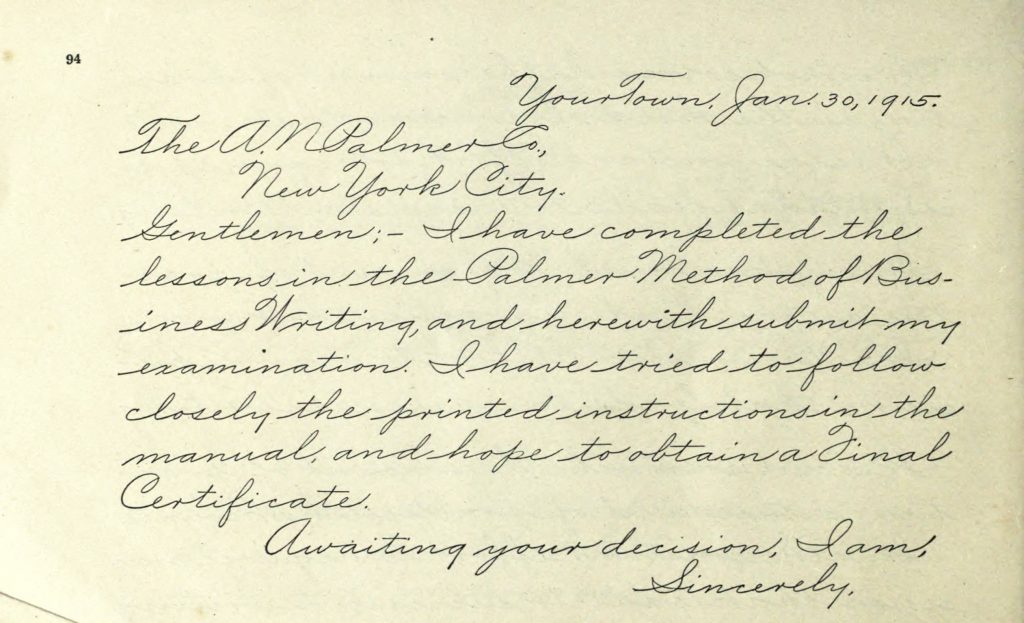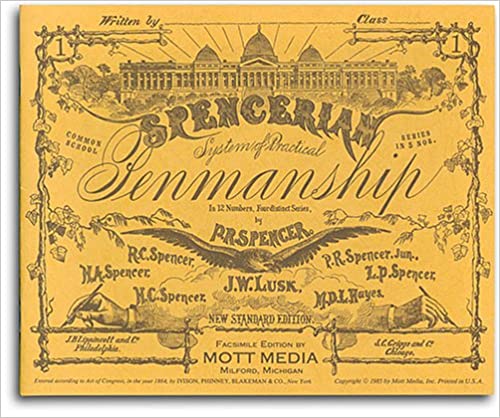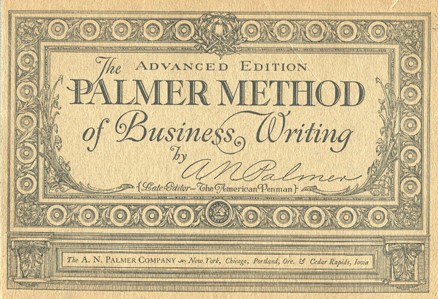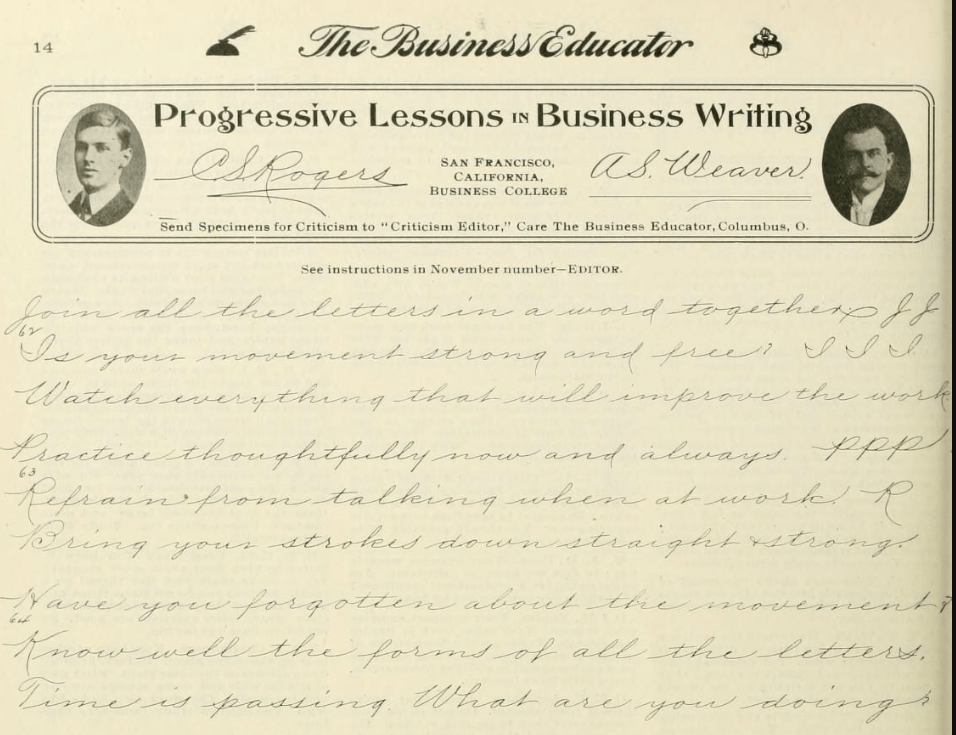
Il y a quelques mois, je vous parlais de mon apprentissage de la Spencerian et de l’écriture cursive américaine. Je vous avais promis un article dédié à cette écriture, le voici enfin ! Préparez-vous à plonger dans l’histoire, au cœur de la révolution industrielle et du développement des affaires !
La Spencerian, une écriture dans son temps
Au cœur de la révolution industrielle
Au début du XIXème siècle, l’écriture enseignée aux Etats-Unis et en Europe était principalement issue de l’Anglaise (ou Copperplate). Avec l’essor de l’industrie et du commerce, les besoins d’écriture pour les affaires se développèrent. Dans les banques, les sociétés de courtage, les assurances, les postes et les industries, la rédaction des contrats, des lettres et la tenue des registres employèrent de nombreuses personnes dont le métier était…d’écrire.
L’essor des plumes métalliques
Concomitamment, dans les années 1830, le procédé de fabrication industriel des plumes métalliques fut au point. Développé par les anglais Gillott et Perry, il offrit une plus grande diffusion des outils d’écriture pour les services administratifs et les écoles, en même temps que de meilleures facilités d’écriture qu’avec la plume d’oie qu’il fallait retailler sans cesse et qui était très fragile.
La naissance de la Spencerian
L’enseignement de l’écriture manuscrite se développa massivement, dans le sillage de la démocratisation de l’enseignement. Savoir écrire devenait un prérequis pour nombre d’emplois administratifs de la société industrielle ainsi qu’un outil d’émancipation sociale.
Vers 1840, Platt Rogers Spencer, un enseignant américain, se consacra à l’étude et la mise au point d’une écriture cursive fonctionnelle qui répondrait mieux aux besoins de l’époque : il simplifia considérablement l’anglaise en s’affranchissant notamment des pleins et déliés, des boucles complexes et des majuscules ornementées. Le système d’écriture qu’il proposa alors privilégiait à la fois la lisibilité, une plus grande rapidité d’exécution, sans sacrifier la beauté calligraphique. Sa méthode devint la norme, et la Spencerian fut enseignée à travers tous les Etats-Unis.
L’héritage de Roger Platt Spencer
Spencer mourut en 1864, mais de nombreux maîtres calligraphes perpétuèrent l’enseignement de sa méthode. Deux des principaux modèles pédagogiques qui ont marqué l’histoire du Spencerian sont les suivants :
La méthode Palmer : business first !
Vers 1890, Austin Norman Palmer édita une méthode d’écriture qui simplifiait encore la Spencerian, avec une méthodologie d’apprentissage privilégiant la posture et le mouvement du bras entier plutôt que le mouvement des doigts et du poignet pour accompagner l’écriture.
La Méthode Palmer fut rapidement reconnue et adoptée, pour sa simplicité et sa rapidité. Elle permettait (presque !) à l’écrivain de rivaliser avec la machine à écrire, mais surtout de pouvoir écrire pendant longtemps sans éprouver de fatigue ou de crispation musculaire. De quoi satisfaire le besoin de productivité des bureaux administratifs et commerciaux : business first !
En 1912, sa méthode fut vendue à plus d’un million d’exemplaires et devint la nouvelle norme d’enseignement de l’écriture aux Etats-Unis jusque dans les années 1950.
Le modèle Zaner-Bloser
Un autre modèle pédagogique important est le Zaner-Bloser, développé par Charles Paxton Zaner et Elmer W. Bloser. Bien que le Zaner-Bloser ne soit pas strictement basé sur le Spencerian, il s’en est grandement inspiré et a incorporé certaines de ses caractéristiques dans un système d’écriture cursive largement utilisé dans les écoles américaines. Ce modèle a également contribué à populariser l’écriture cursive et a apporté des améliorations pour s’adapter aux besoins des élèves.
Caractéristiques de l’écriture Spencerian
Le Spencerian se caractérise par des traits élégants, des courbes douces et un aspect fluide qui donne à l’écriture une touche artistique. Voici quelques-unes des principales caractéristiques de cette écriture :
Formes courbes et gracieuses
Les lettres de la Spencerian sont principalement formées de courbes gracieuses, ce qui donne à l’ensemble de l’écriture un aspect harmonieux et élégant. Les lignes fines et les boucles délicates lui confèrent une beauté artistique qui la distingue des styles d’écriture plus rigides.
Connexions fluides
Un aspect essentiel du Spencerian est la liaison fluide entre les lettres. L’écriture est conçue pour être réalisée d’un seul trait, sans lever le stylo, créant ainsi une continuité esthétique entre les caractères.
Inclinaison de l’écriture
La Spencerian est généralement écrite avec une inclinaison vers la droite, ce qui ajoute à son élégance et à son allure dynamique. Cette inclinaison permet également d’améliorer la fluidité des mouvements lors de l’écriture.
Flexibilité du tracé
Une autre caractéristique distinctive du Spencerian est le contraste entre les traits épais et fins. Les lignes sont tracées avec un stylo ou une plume flexible, permettant de créer des variations de largeur en fonction de la pression exercée sur l’outil d’écriture. Pour l’écriture de tous les jours, la Spencerian peut être tracée en monoligne, sans pleins et déliés, tout en conservant son élégance.
The Wesco System of Writing, toujours sur le site de David Grimes.
Dans les ouvrage plus récents, j’ai aussi travaillé avec le livre de Michael Sull : The Art of Cursive Penmanship: A Personal Handwriting Program for Adults.